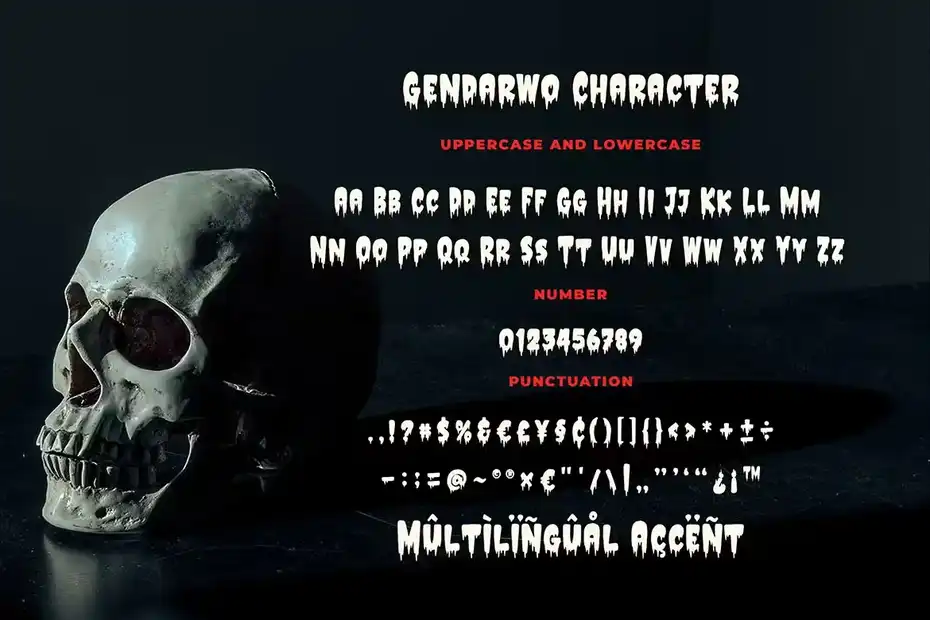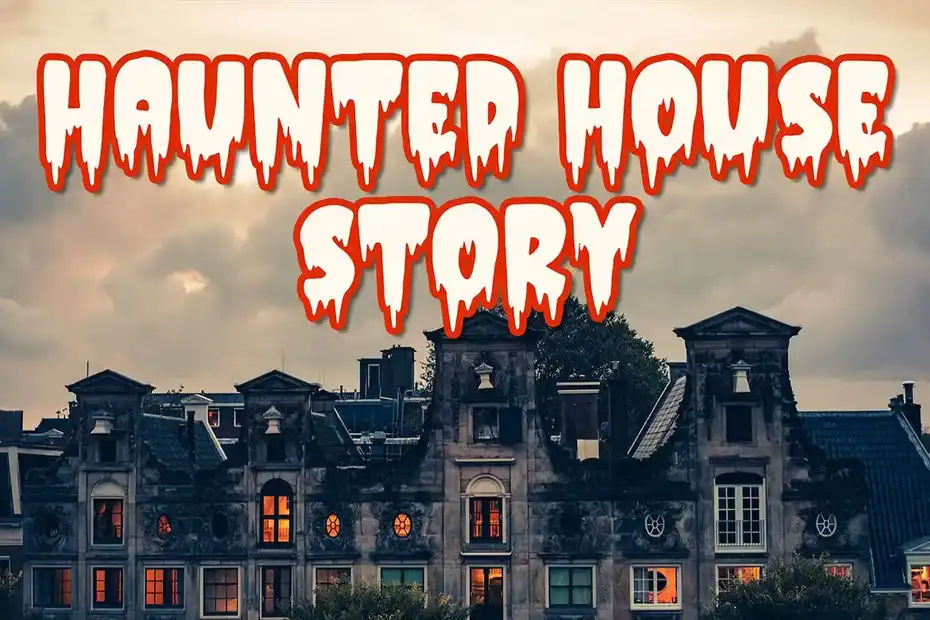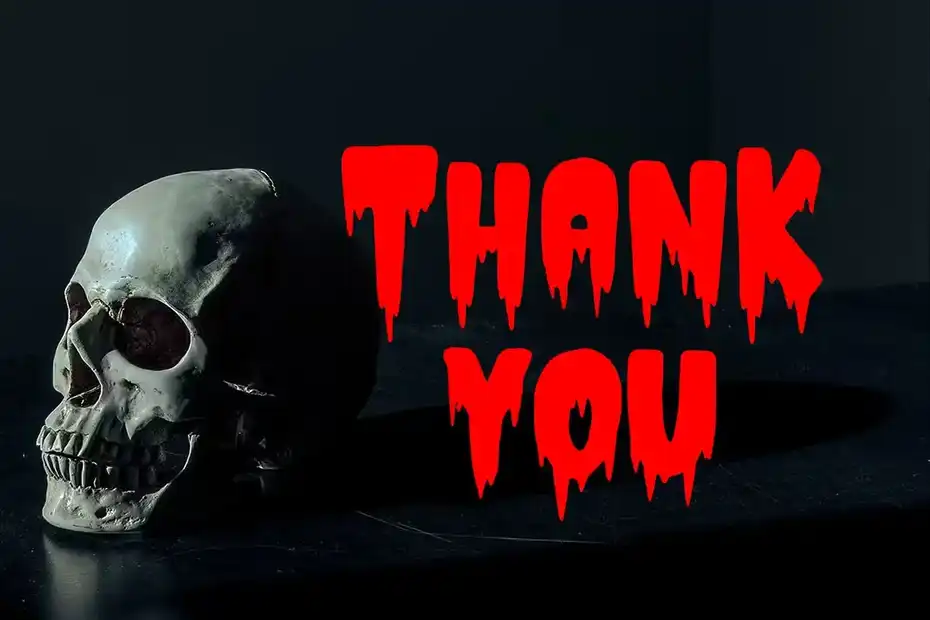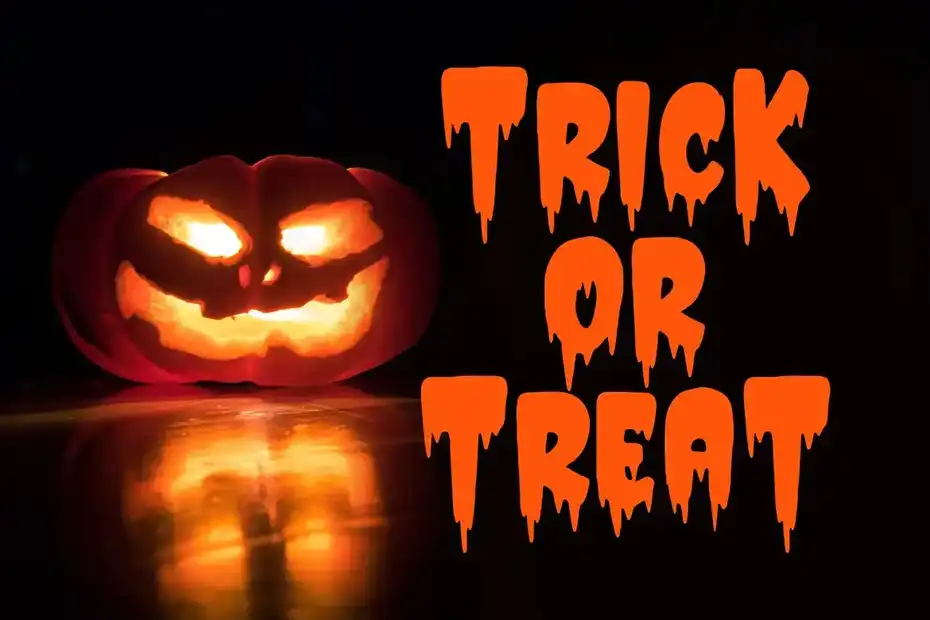
فونت انگلیسی ترسناک Gendarwo – Scary Typeface : این مجموعه شامل یک فونت انگلیسی ترسناک است که برای پوستر فیلم ترسناک مناسب میباشد.
- عنوان مجموعه: Gendarwo – Scary Typeface
- سبک: Serif
- فضا بین حروف: معمولی
- اندازه بهینه: تمامی سایز ها